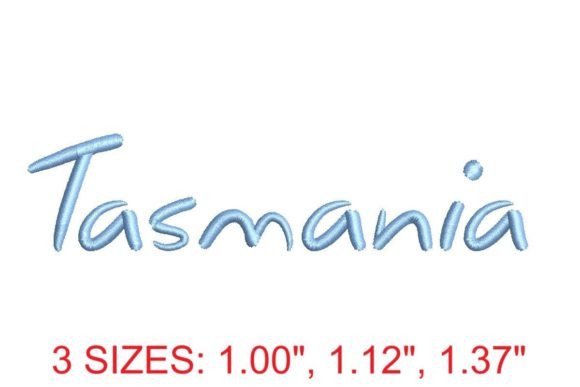
Tasmania Font
إذا كنت تبحث عن أصول عالية الجودة مثل Tasmania Font، فإن هذه الحزمة المميزة هي خيار رائع لمشاريعك الإبداعية.
Who Is This Best For?
سواء كنت تقوم بإنشاء منتجات الطباعة عند الطلب أو دعوات الزفاف أو رسومات وسائل التواصل الاجتماعي، فإن Tasmania Font هو الخيار المثالي.